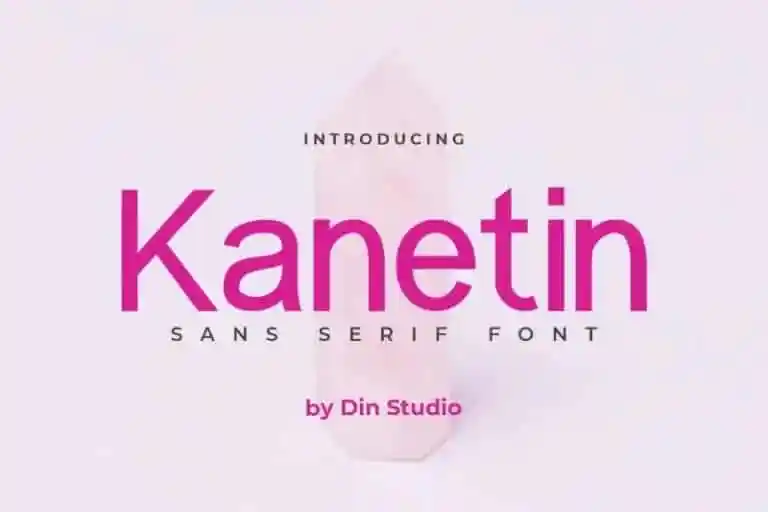
Kanetin Sans Serif Font – Download Grátis
A Kanetin Sans Serif Font é uma elegante tipografia de sans serif perfeita para projetos profissionais que precisam de uma identidade visual única e sofisticada. Ela foi criada pelo font designer Din Studio, oferecendo um equilíbrio harmonioso entre classe e simplicidade. Esta fonte é perfeitamente adaptada para uso em logos, marcas de marca, e até mesmo em citações ou frases especiais, garantindo que cada caracter possua uma personalidade única e bonita. Ideal tanto para impressão quanto para criação de identidades digitais, a Kanetin Sans Serif oferece um amplo leque de opções. Seja você criando logos contemporâneos ou procurando por elementos gráficos inovadores para seu próximo projeto, esta fonte é uma escolha confiável e moderna. Sua facilidade na aplicação em diversos formatos garantirá que sua mensagem seja transmitida com estilo, elegância e personalidade.